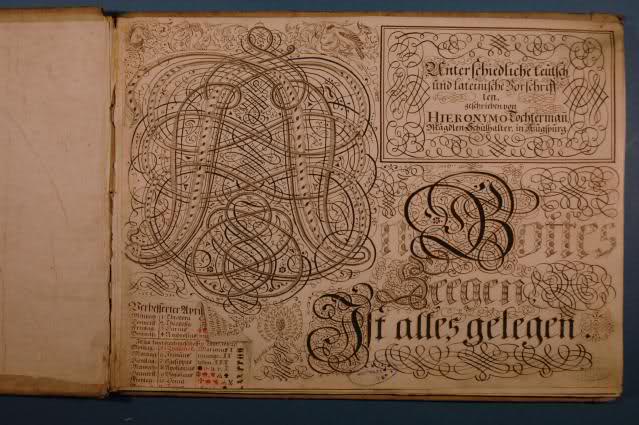
Schreibmeisterbuch von 1739
Ich habe heute in meiner Bibliothek ein Schreibmeisterbuch gefunden - das musste ich sofort fotografieren. Hier ein Beispiel. Alle neun Blätter sind auf flickr unter
Das Buch ist 1739 von Hieronymus Tochterman in Augsburg geschrieben
:biglove: und ein feines Beispiel das sich gedruckte Schrift in den letzten 270 Jahren kaum geändert hat und bestens für die Nachwelt lesbar blieb. Möchte mal wissen, ob in 270 Jahren unsere aktuellen Informationsträger noch lesbar sind.